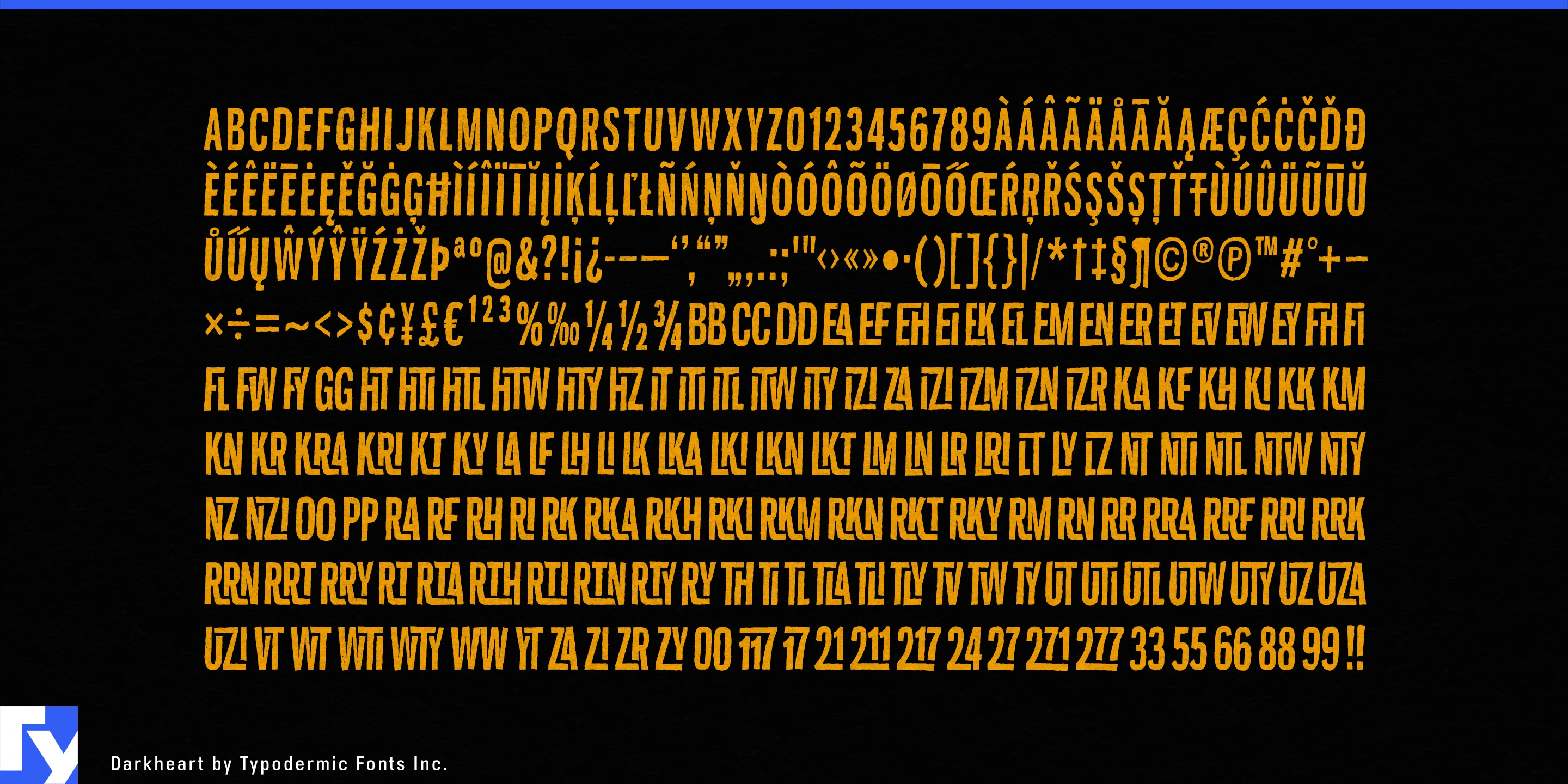
Darkheart
Darkheartは、紙から切り出して手で組み合わせたような、背が高く傾いたストロークで描かれたオールキャップスのホラー書体です。吸血鬼の城、放射能で生まれた怪物、宇宙人の侵略、幽霊の出る研究所、真夜中を過ぎてからの言葉にできない恐怖を予告する映像。1960年代のドライブインシアターが本来の居場所です。ホラー映画のポスター、配信サムネイル、予告編のタイトル、漫画の題字、ペーパーバックの表紙、VHSやBlu-rayの復刻版に、手作りのタイトルカードのような詰まった緊迫感を与えます。
ハロウィーンには、Darkheartが活躍できる場面が一シーズン分あります。お化け屋敷のポスター、迷路の看板、怪談ツアーの広告、脱出ゲームのアイデンティティ、仮装パーティーの招待状、ホラーイベントの日程、遊園地の恐怖演出ナイトには、何の催しかをひと目で伝える文字が役立ちます。流れる血やゴシック装飾に頼らないため、色とイラスト次第で本格的な脅威から、ユーモラスな怪物、子ども向けの少し不気味なイベント、遊び心のある季節限定パッケージまで表情を変えられます。
切り紙のような緊張感は、定番のホラー以外にも合います。実録犯罪のポッドキャスト、カルト集団を扱うドキュメンタリー、未確認生物の調査、超常現象のシリーズ、都市伝説のアンソロジー、心理スリラーでは、不安定な証拠や急いで組み立てた見出しを思わせます。ミュータント、制御を失った実験、冷戦期の疑心暗鬼、管理の行き届かない宇宙船を描くB級SFも、同じ視覚世界に属します。
幅の狭いプロポーションにより、意外に長いタイトルも、コンパクトなポスターの枠、書籍の表紙、動画のフレーム、商品ラベルに収まります。不揃いな字幅、傾いた縦線、鈍い角、変化するストロークの密度が、行を機械的なリズムに落ち着かせません。内蔵された豊富な合字は、よく現れる文字の組み合わせを傾いた連結形にし、特注レタリングのように組み合わされた印象を与えます。幅狭の大文字を短くまとめた文章でもまとまりが保たれるため、予告編のタイトルカード、不穏な警告、エピソードの紹介文、漫画のナレーションに使えます。